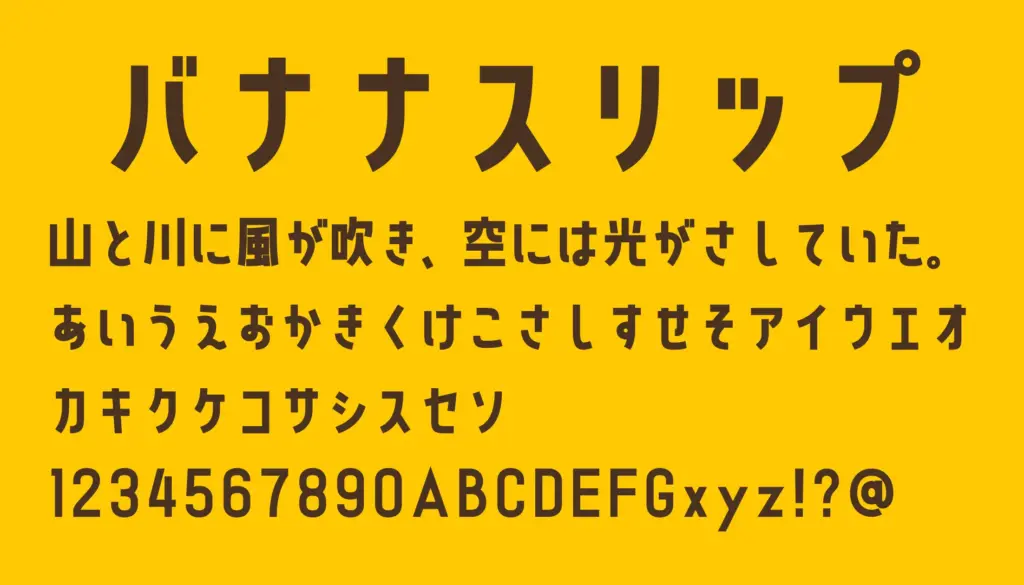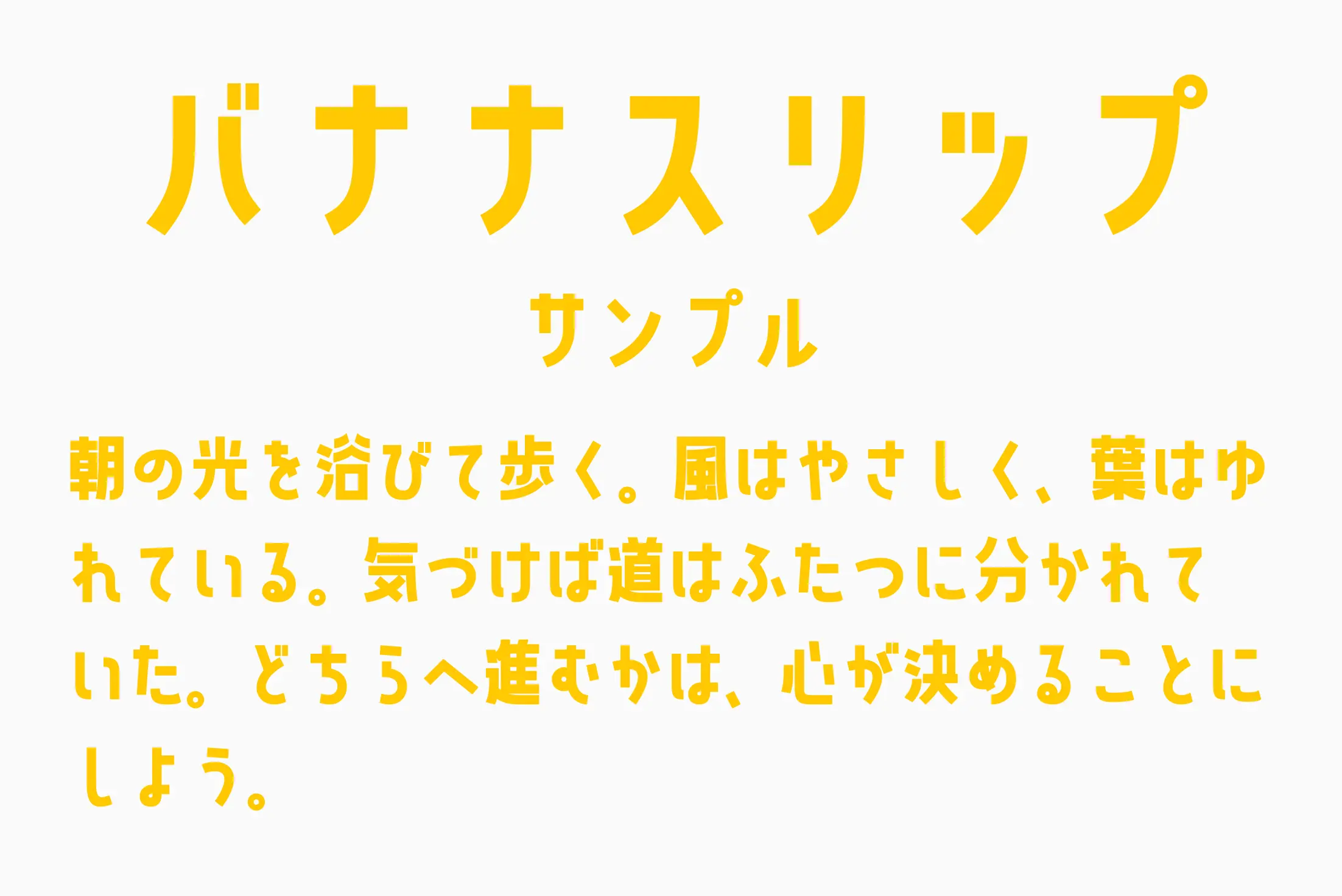
骨太で力強い印象を持ちながらも、どこか愛嬌のある日本語フォントです。太めのゴシック系書体に独自の丸みを加え、視認性の高さと親しみやすさを両立。ロゴやタイトル、YouTubeサムネイルなどインパクト重視のデザインに最適です。商用利用も可能で、動画やバナー、ポスターなど幅広い場面で活躍します。
バナナスリップ